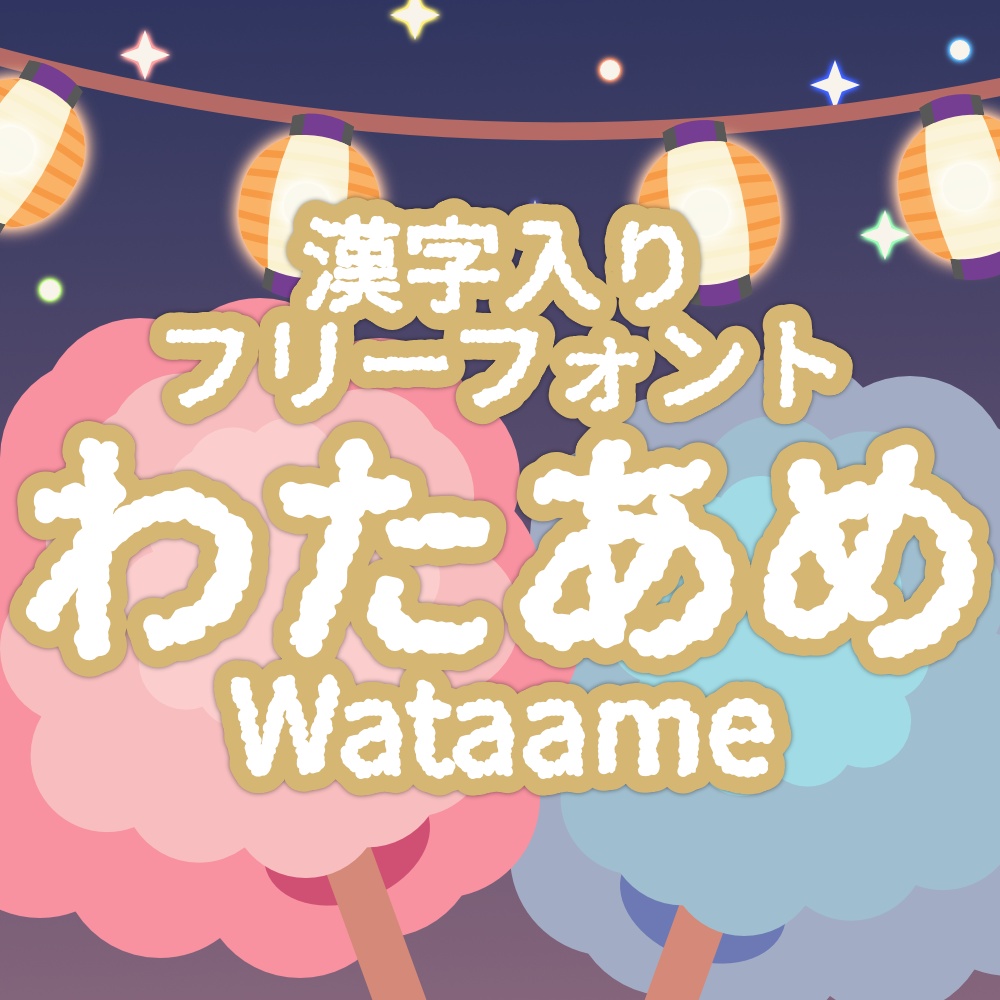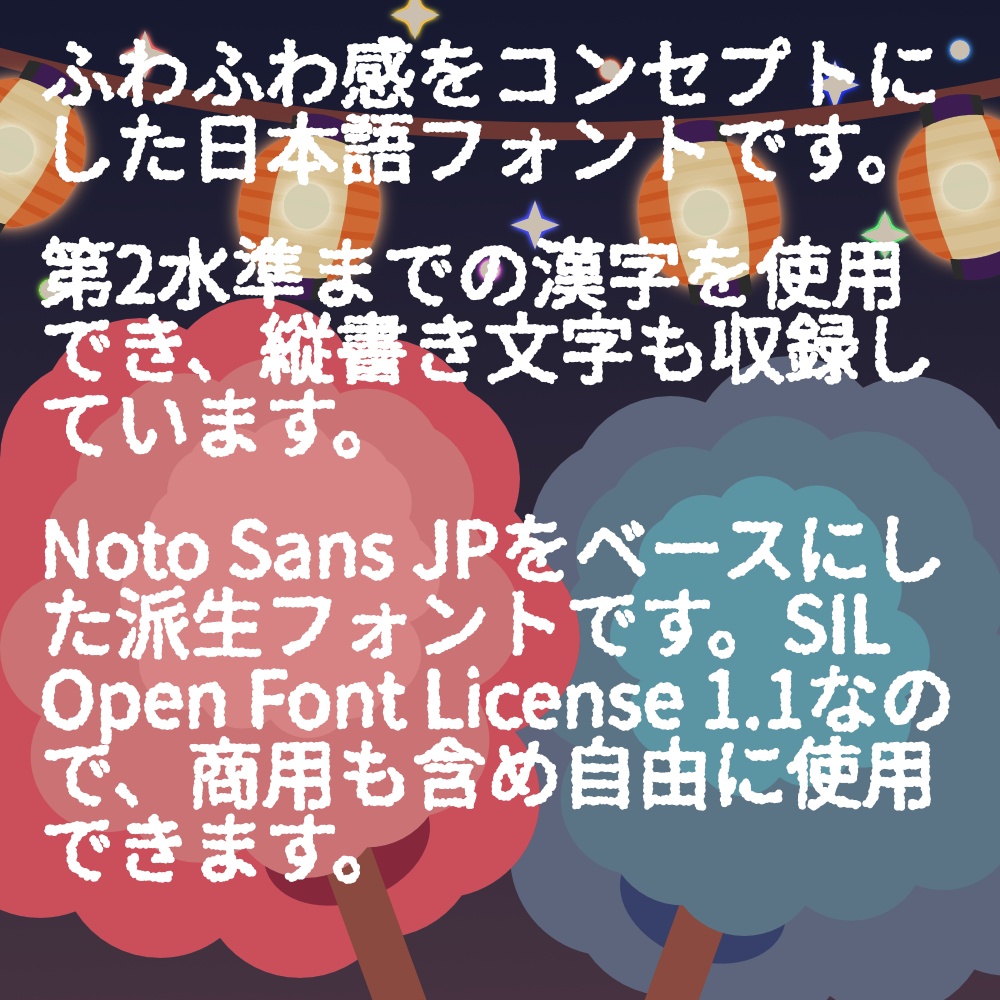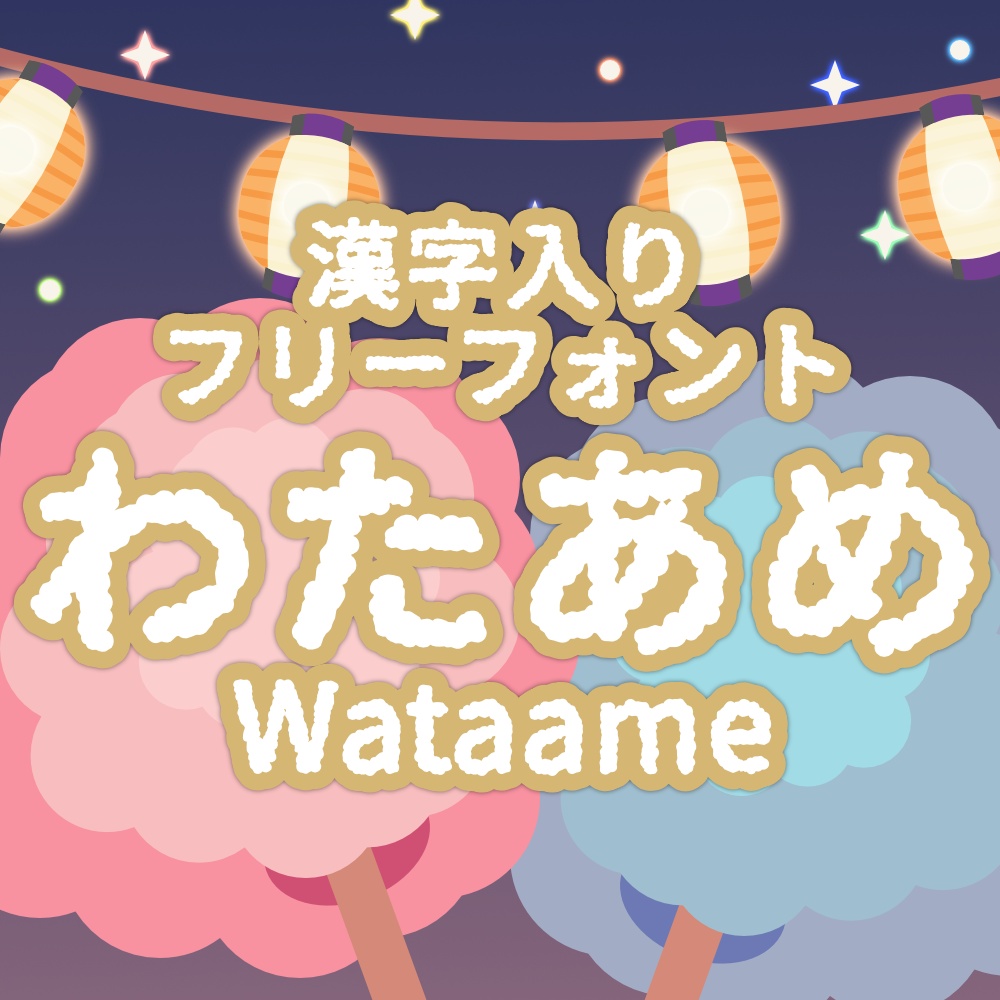
フォント Wataame わたあめ
ふわふわ感がコンセプトです Notoフォントで遊ぶプロジェクト第1弾。 次回は9/11を予定しています。 <<<バージョンが1.1になりました。グリフのサイズが大きくなって流用元と同じになる破壊的変更があります。旧バージョンをお持ちの方は再ダウンロードをお願いします。>>>
2026/09/18 1.1 全体的なグリフ修正 v1.0と互換性はありません - はみ出し処理を見直し、グリフの大きさの派生元フォント比率を95%から100%にした(罫線が左右繋がるようになりましたが、左右にはみ出すようになります) - 乱数シードを固定から中間ファイル名由来のハッシュ値に変更した(偏が同じ漢字で同じ形になる可能性が無くなりました) 2026/09/09 1.0c ドキュメント修正 - OFL.txtを見直し 2026/08/31 1.0b グリフ修正 - 一部グリフの縦送り幅が不正になっていたのを修正 - ライセンス周りのドキュメントを少し見直した 2026/08/29 1.0a グリフ修正 - 派生元フォントで左側にはみ出しているグリフ[j]等について、右側にずれてはみ出ていたのを修正した 2026/08/28 1.0 初版